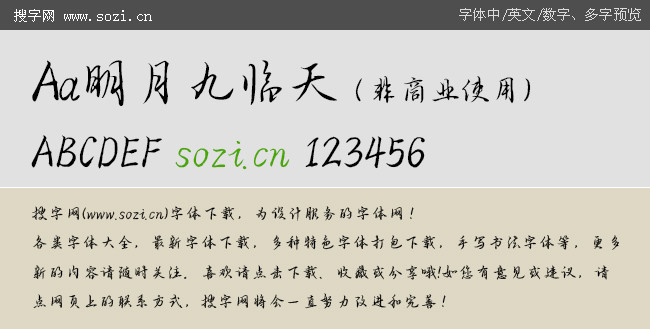
Aa明月九臨天
搜字網(wǎng)給大家提供一款A(yù)a明月九臨天(非商業(yè)使用)中文字體下載,該字體是一款手寫風(fēng)格的字體,字體筆觸較為纖細(xì)靈動(dòng),字形灑脫,流暢自然,具有很好的視覺(jué)感。適合書裝設(shè)計(jì)、包裝設(shè)計(jì)、海報(bào)設(shè)計(jì)等應(yīng)用(此字體為個(gè)人非商用版,商用可以聯(lián)系QQ:1006760504)。